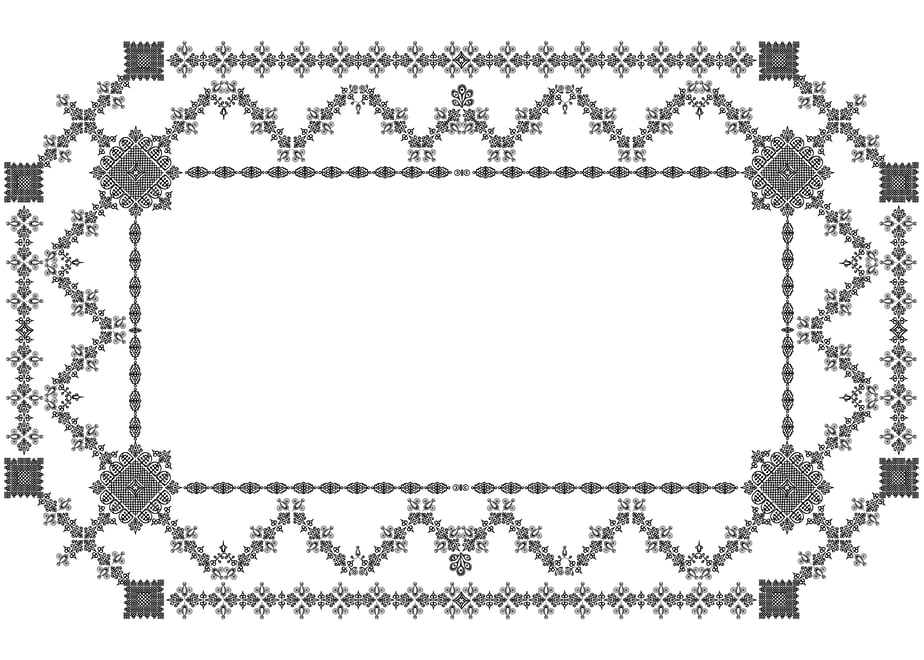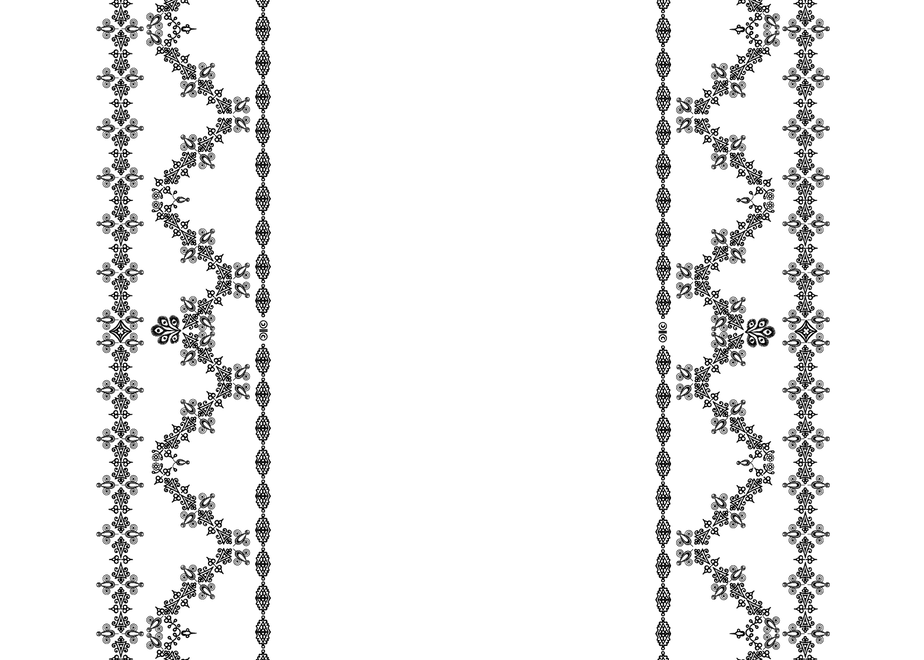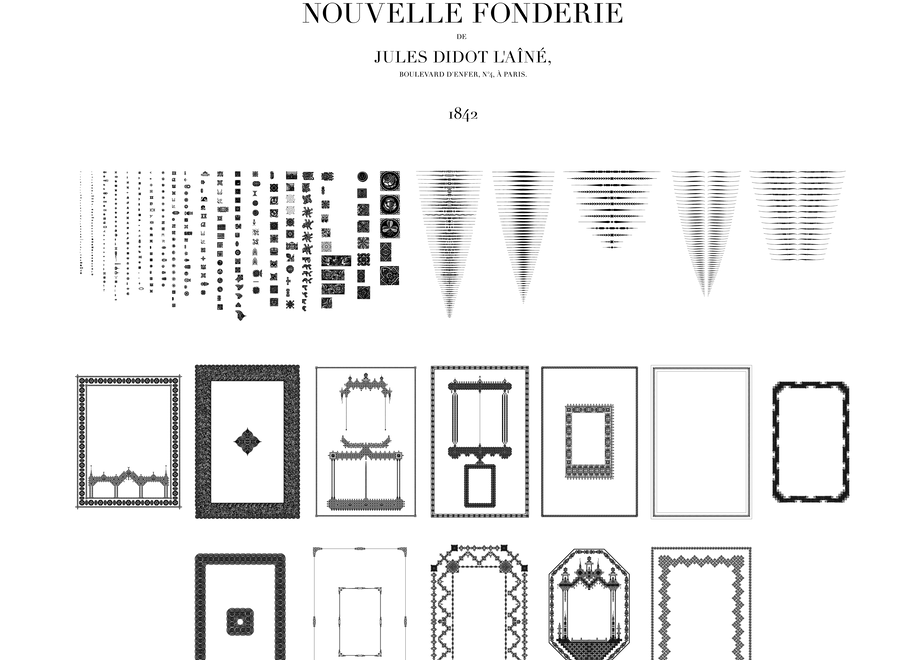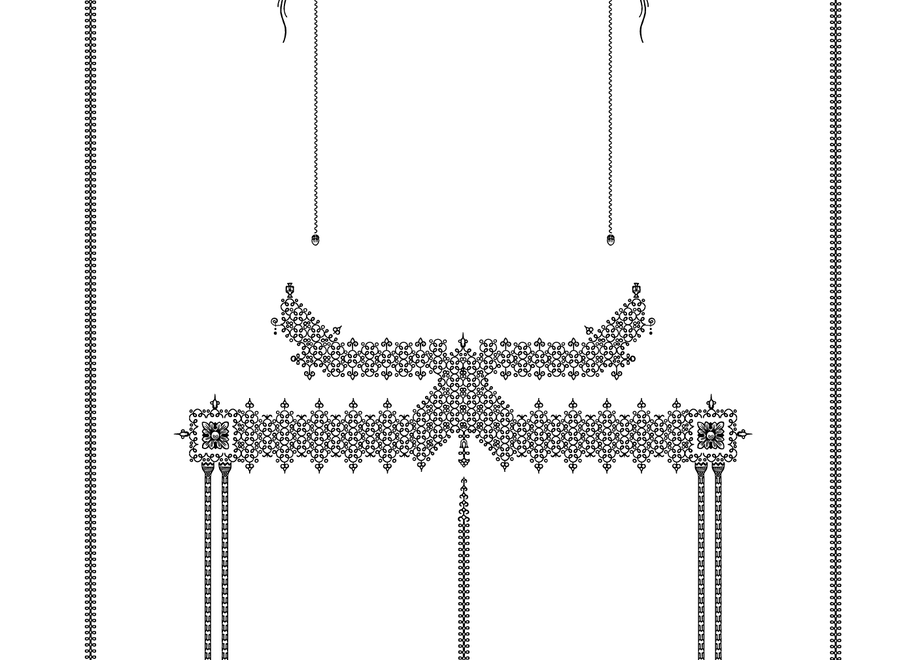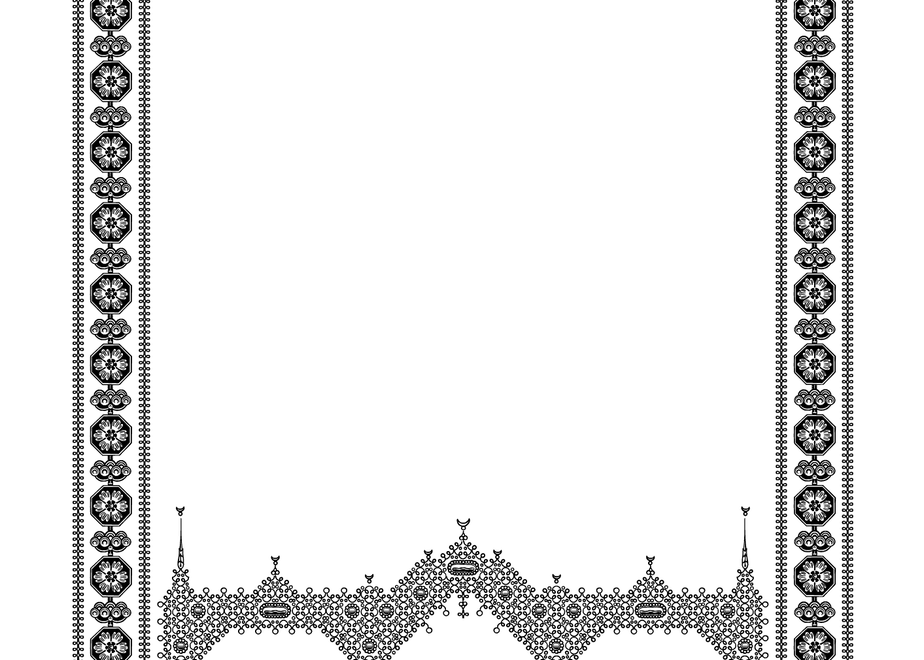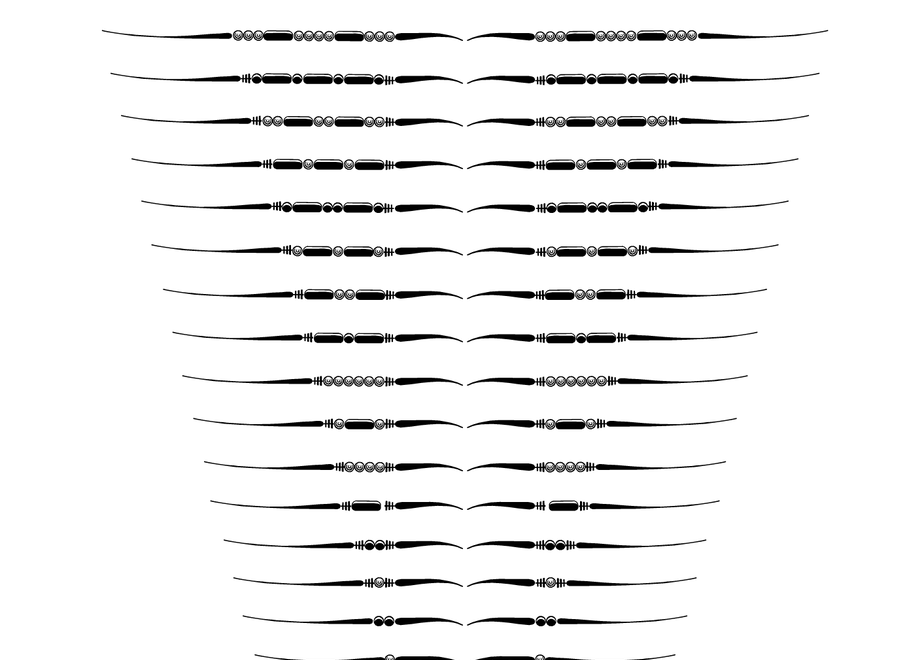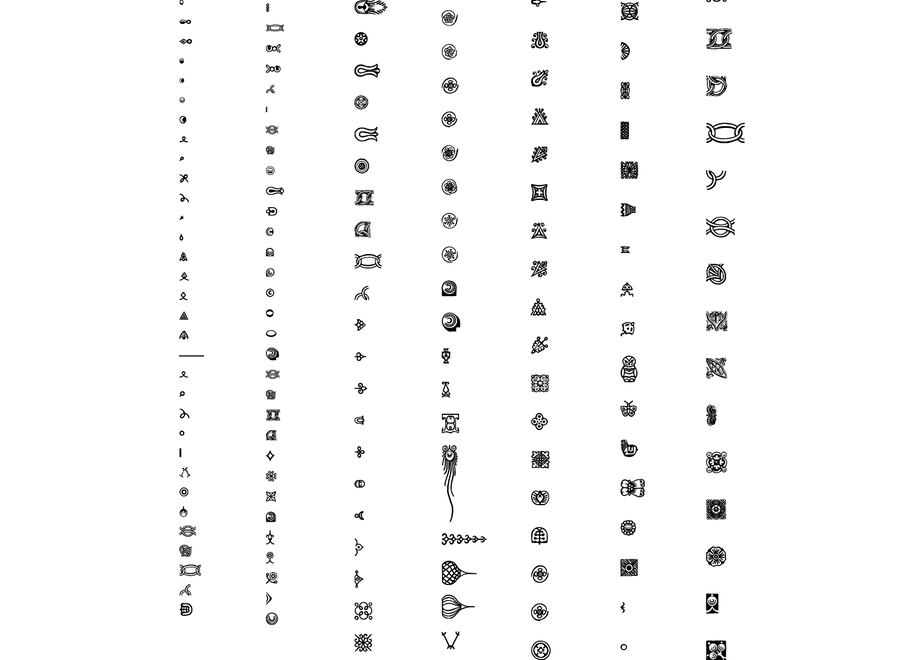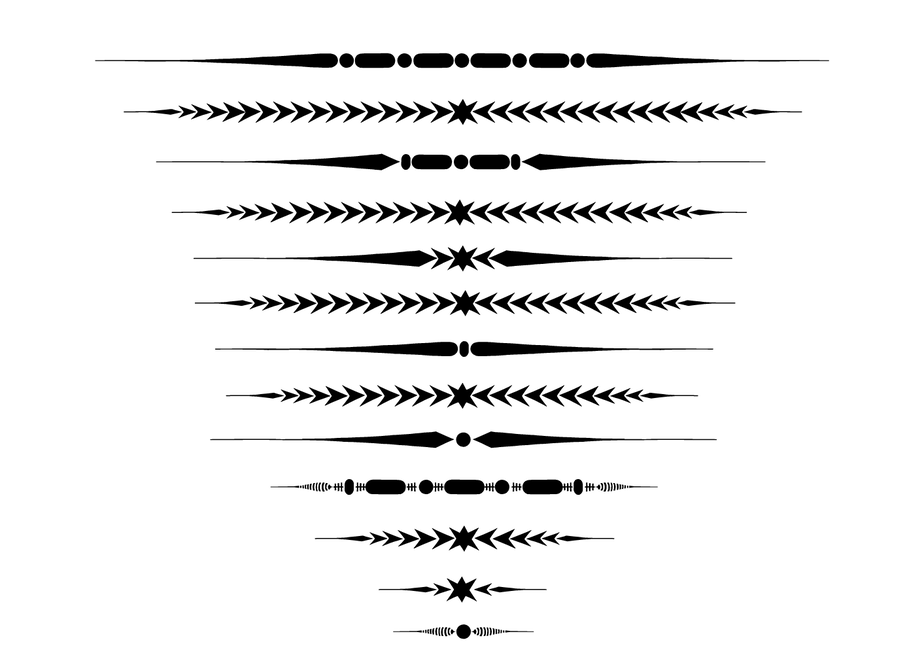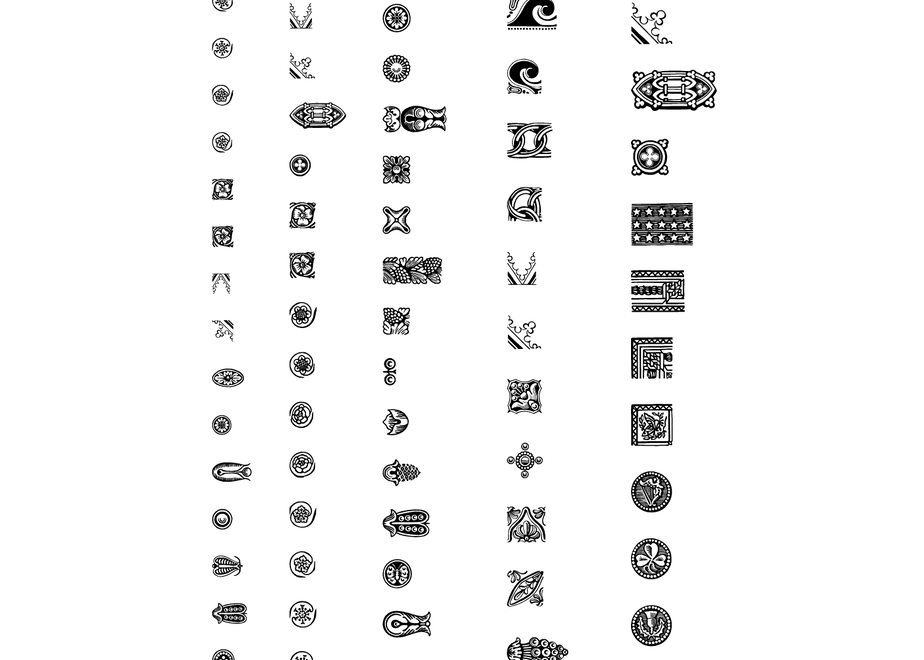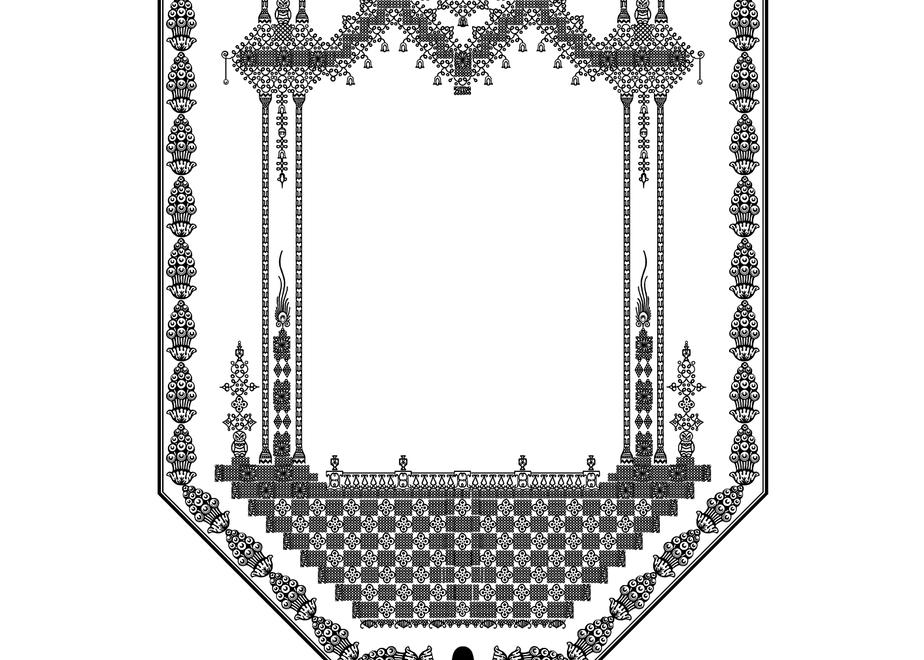
装飾活字:SPÉCIMEN DE LA NOUVELLE FONDERIE DE JULES DIDOT L'AÎNÉ, BOULEVARD D'ENFER, N°4, À PARIS. 1842
1842年に発行された「SPÉCIMEN DE LA NOUVELLE FONDERIE DE JULES DIDOT L'AÎNÉ, BOULEVARD D'ENFER, N°4, À PARIS. 1842」に収録された花形装飾活字および装飾罫線をもとに、現代のデザイン環境で利用できるよう再構築したデータパッケージです。
資料に収録された装飾の形状や構成を可能な限り保持しながらデジタル化を行い、グラフィックデザイン、エディトリアルデザイン、ロゴ制作、パッケージデザインなど幅広い用途でご利用いただけます。
本プロジェクトは、フランスの美術大学図書館でデジタルアーカイブに携わる方とのご縁から始まりました。高解像度でスキャンされた原典資料をご提供いただき、そのデータをもとに一点ずつ手作業で調整を行い、Adobe Illustratorでアウトライン化しています。
Jules Didot が設計した見本帳に収録された装飾活字および装飾罫線を全て採録し、現代のデザインワークで活用できる形に再構築しました。
本商品は、1842年にフランスで発行された Jules Didot の活字見本帳をもとに制作したアーカイブコレクションです。
花形装飾活字だけでなく、豊富な装飾罫線が収録されていることが大きな特徴であり、19世紀フランス印刷文化の意匠を現代のデザイン制作へ取り入れることができます。